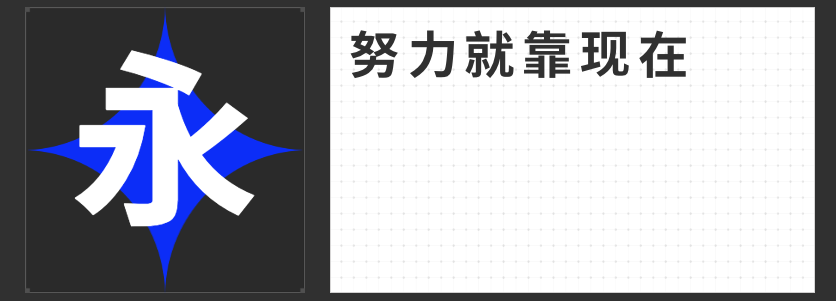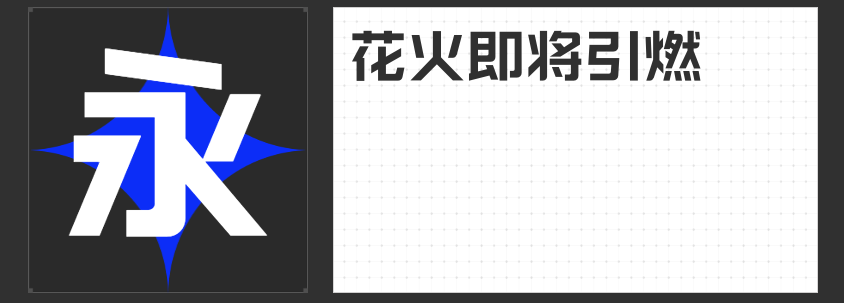
设计中的黑体之选!风格各异,快来试试吧
在设计的世界里,字体如同色彩与形状,是表达创意与情感的重要元素。黑体字体,以其简洁、醒目、易读的特点,在设计领域中扮演着不可或缺的角色。今天,我们为大家推荐四款适用于设计的黑体字体,它们各具特色,能够为您的作品增添独特的韵味。
一、字圈也字时代黑体
字圈也字时代黑体,一款融合了时代印记与创新精神的黑体字体。其笔画端口特有的喇叭口形状装饰,源自早期铅字印刷字体的演变,这一设计不仅解决了当时技术限制下笔画端口收缩的问题,更赋予了这款字体独特的视觉美感。字形规矩方正,端庄而不失活泼,喇叭口装饰的融入,使得整体设计更加生动有趣。
励字勇敢黑简 大黑,一款以粗壮有力著称的黑体字体。没有衬线装饰,笔画简洁明了,撇捺等笔画不尖,易于阅读。横直均匀,突出醒目,常用于标题、导语、标志等设计场景,能够迅速吸引观众的注意力。其粗犷的笔触,传递出一种坚定与勇敢的力量感。
三、励字综艺简繁
励字综艺简繁,一款活泼严谨并存的黑体字体。笔划更粗,空间充满,拐弯处处理圆润方正,既保持了黑体的规矩之美,又增添了艺术性的灵动。笔画粗犷而不失细腻,横平竖直,整体设计既严谨又活泼,非常适合用于综艺、广告等富有创意的设计场景。
四、励字超粗黑简繁
励字超粗黑简繁,一款充满力量感的标题黑体字。其设计并非完全的正方形,笔画带有斜度,营造出一种动感与活力。横竖笔形粗细视觉相等,笔形方头方尾,黑白均匀,非常醒目。广泛适用于各种设计场景,能够迅速抓住观众的眼球,传递出强烈的视觉冲击力。
这四款黑体字体,各具特色,无论是时代印记的融入,还是力量感的传递,都能为您的设计作品增添独特的魅力。希望这些推荐能够激发您的设计灵感,让您的作品更加出彩。